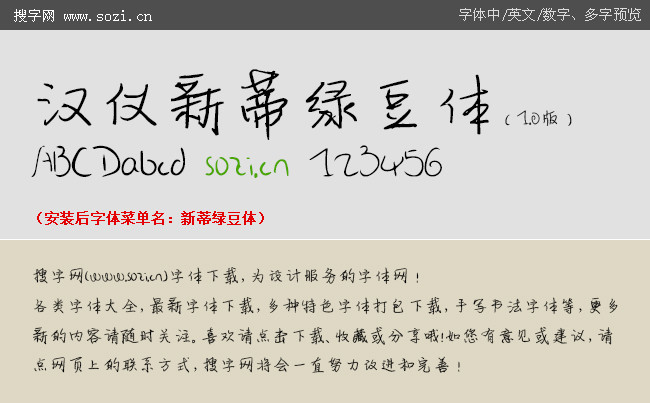
漢儀新蒂綠豆體1.0
搜字網(wǎng)提供一款漢儀新蒂綠豆體1.0字體下載,漢儀新蒂綠豆體是一款漂亮的手寫風(fēng)格藝術(shù)字體。由漢儀新蒂工作室出品,漢儀新蒂工作室成立于2016年,由漢儀字庫(kù)與新蒂字體聯(lián)合成立,本字體字形流暢大方,適合應(yīng)用于海報(bào)設(shè)計(jì)、藝術(shù)設(shè)計(jì)、包裝設(shè)計(jì)等應(yīng)用。(本字體為個(gè)人非商用版,如需要商用請(qǐng)聯(lián)系漢儀公司購(gòu)買版權(quán))